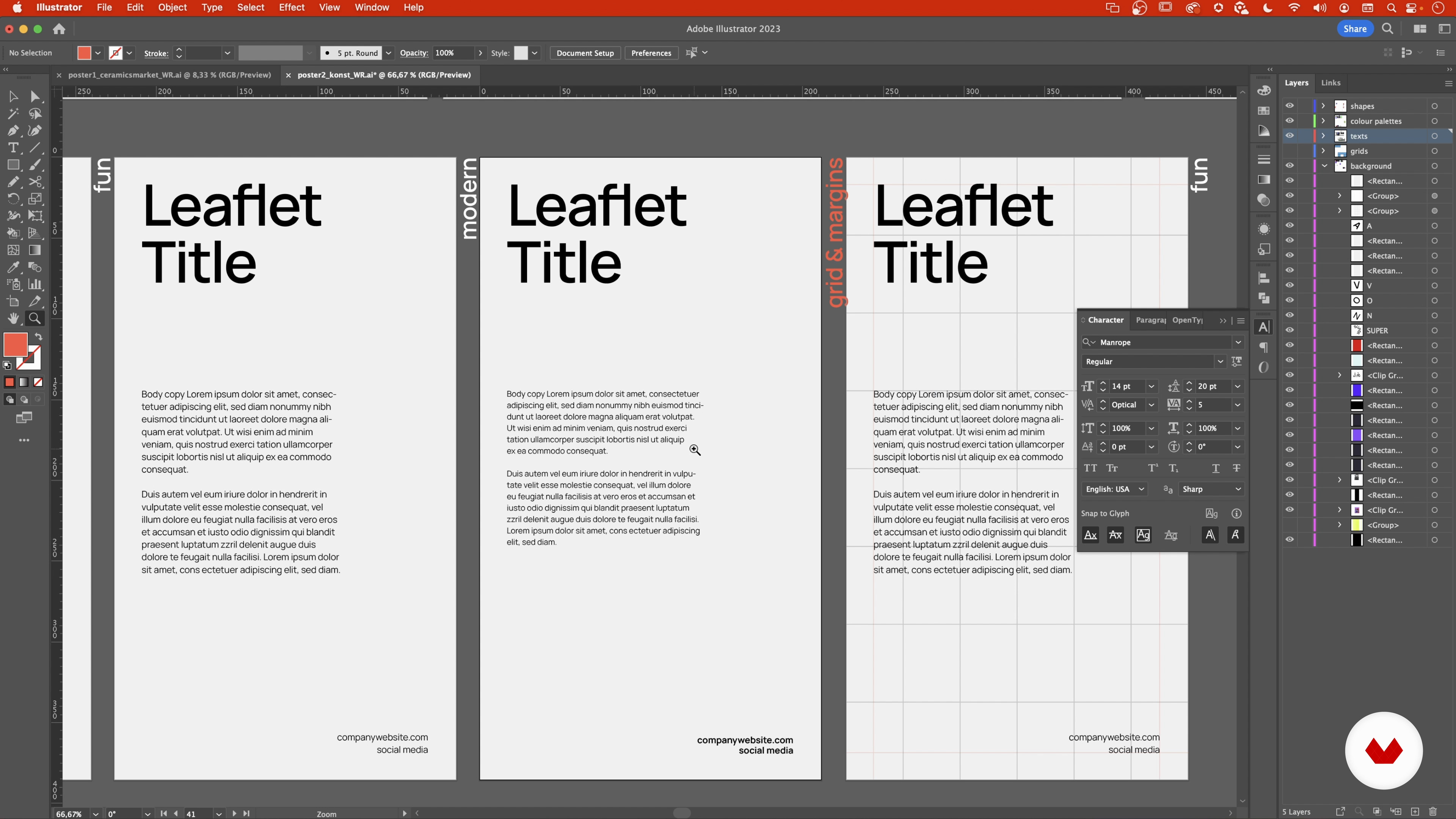
Personalidades tipográficas
Sobre a videoaula: Personalidades tipográficas
“Agora irei trabalhar com tipografia no Adobe Illustrator. Você aprenderá como escolher a fonte certa para 3 cenários imaginários. Usarei um design de folheto simples para testar minhas ideias tipográficas. ”
Nesta videoaula, Weronika Rafa aborda o tópico: Personalidades tipográficas,que faz parte do curso online da Domestika: Introdução ao design gráfico para quem não é designer. Descubra a arte do design e crie pôsteres incríveis usando cor e tipografia..
“nesta lição. Vamos falar sobre por que escolher um tipo de personalidade é importante. Para fazer isso. Faremos alguns exercícios. Existem tantas escolhas e características diferentes de fontes. Para ser sincero. às vezes é avassalador escolher a opção correta. Às vezes. é complicado. o processo de decidir o final. e não apenas a fonte. é um desafio importante. Para empresas maiores. o processo pode demorar dias ou até semanas para ser concluído. O que eu estava pensando em fazer era preparar um pequeno exercício. utilizando elementos do pôster dois e conteúdo fictício. Para observar. Como ...”